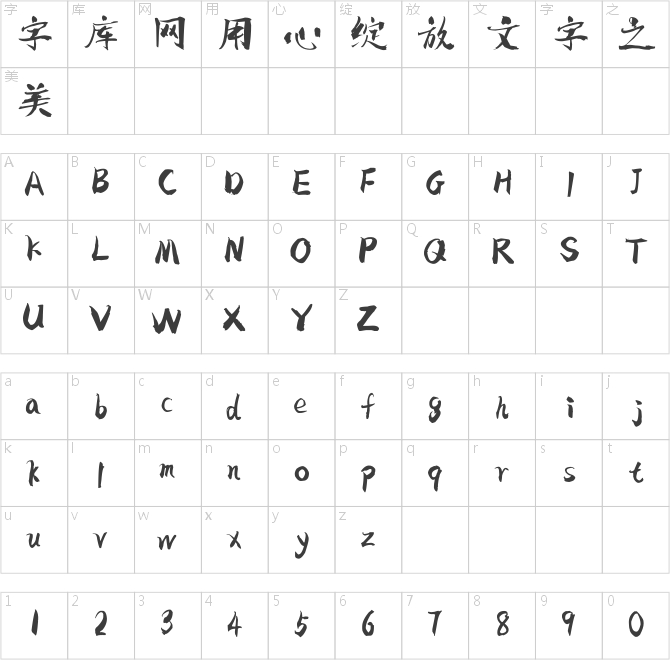
南構(gòu)鮑貴芬心然體 詳情頁(yè)
南構(gòu)鮑貴芬心然
南構(gòu)字庫(kù)
南構(gòu)鮑貴芬心然體字體字庫(kù)是一款讓人賞心悅目、百看不厭的中文字體,適合各類(lèi)廣告和產(chǎn)品包裝設(shè)計(jì)應(yīng)用,字體大小5.23MB,格式為ttf字體,上傳用戶(hù)是那是不變的,作者/版權(quán)方為南構(gòu)字庫(kù)